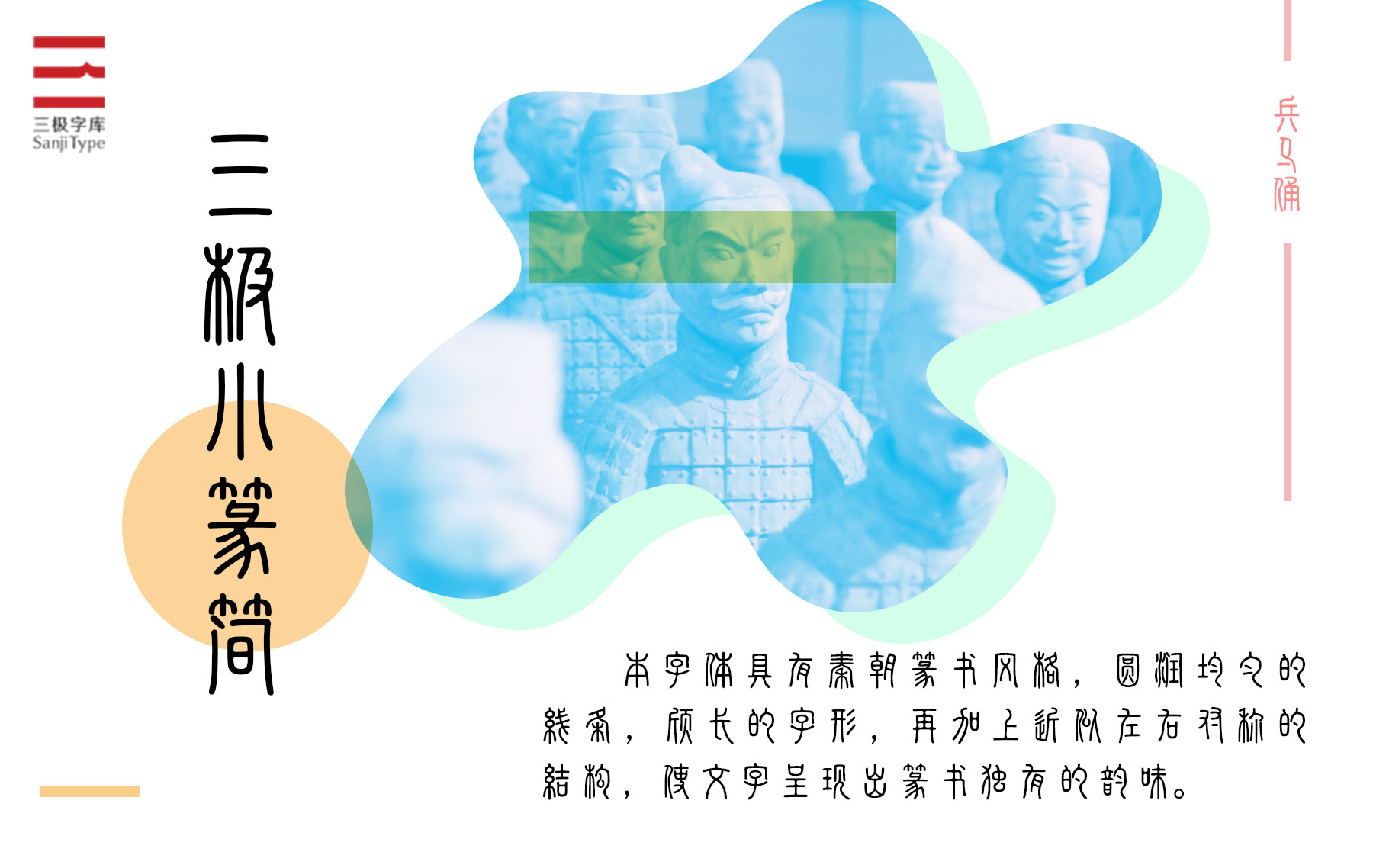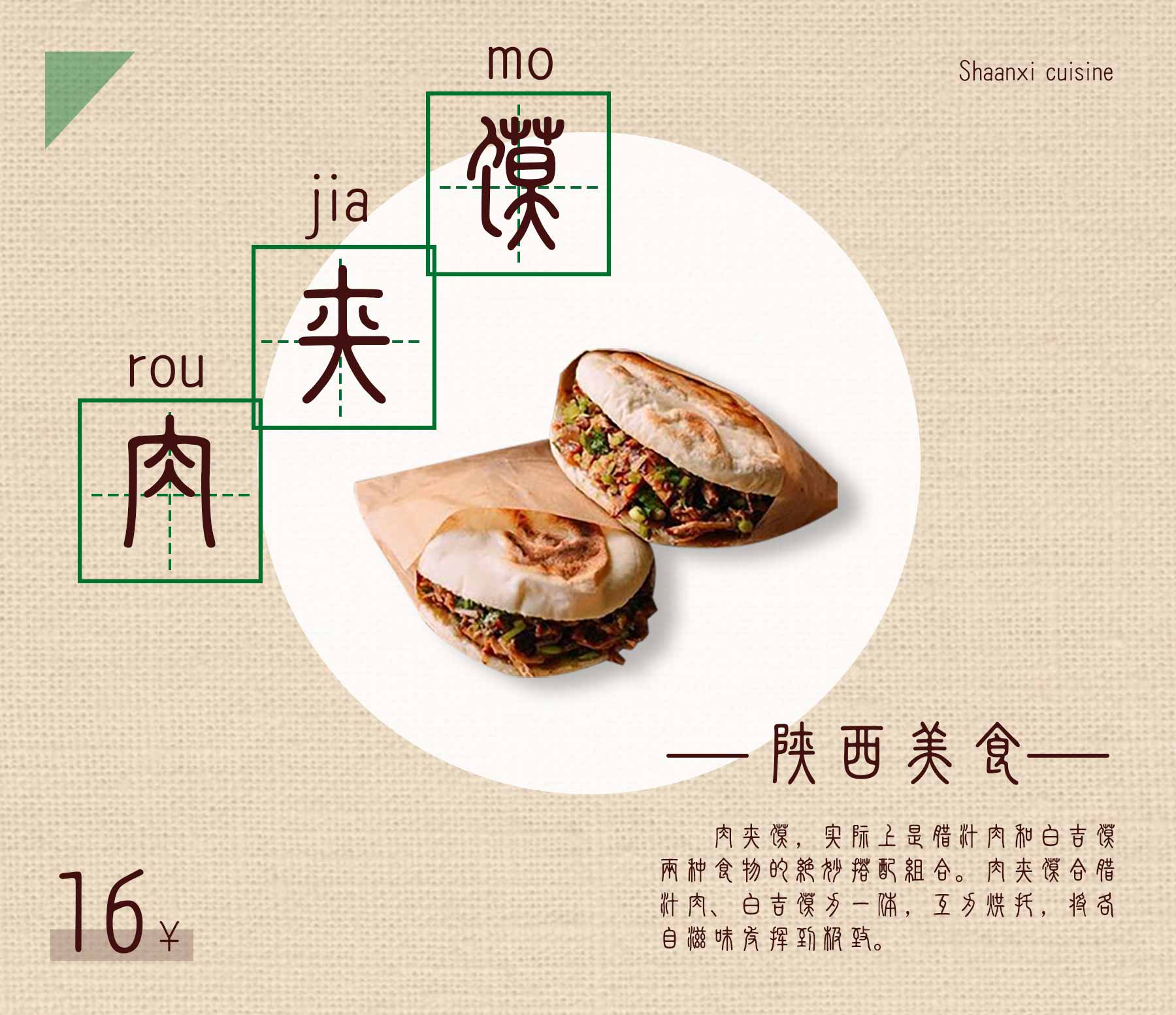
三极小篆简
篆书起源于西周末年,东周时在秦国流行,至秦始皇时达到鼎盛,汉代开始衰退。东周(即战国)时的篆书为大篆,称始皇时的篆书为小篆,称汉代篆书为汉篆。
本字体具有秦朝篆书风格,圆润均匀的线条,颀长的字形,再加上近似左右对称的结构,使文字呈现出篆书独有的韵味。
本字体适合应用在春联、喜帖、菜单、印章及书刊杂志等。